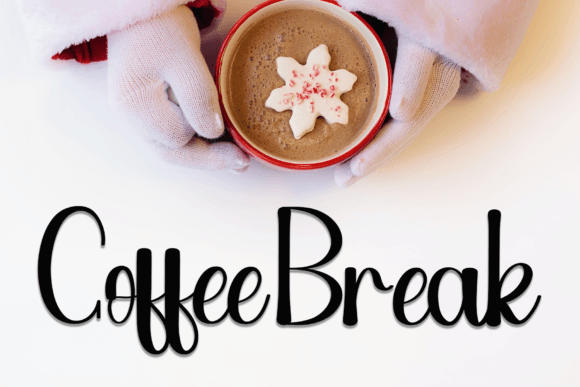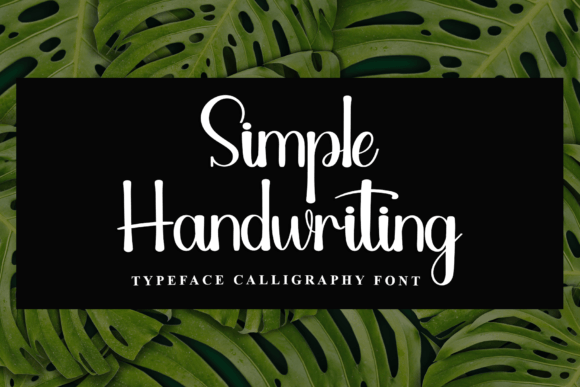
手寫英文字體
今天 Creative Fabrica 限時免費送出的 Simple Calligraphy 字體,原價 $16 美元,字體風格很有節日感,並帶著手寫毛筆字的溫度。限時 24 小時免費,還附帶終身商業授權。
字體介紹
由設計師 Inermedia STUDIO 打造,字體屬於書法手寫字體,而風格上可以用節慶、溫暖、帶有懷舊感來形容。
字型預覽